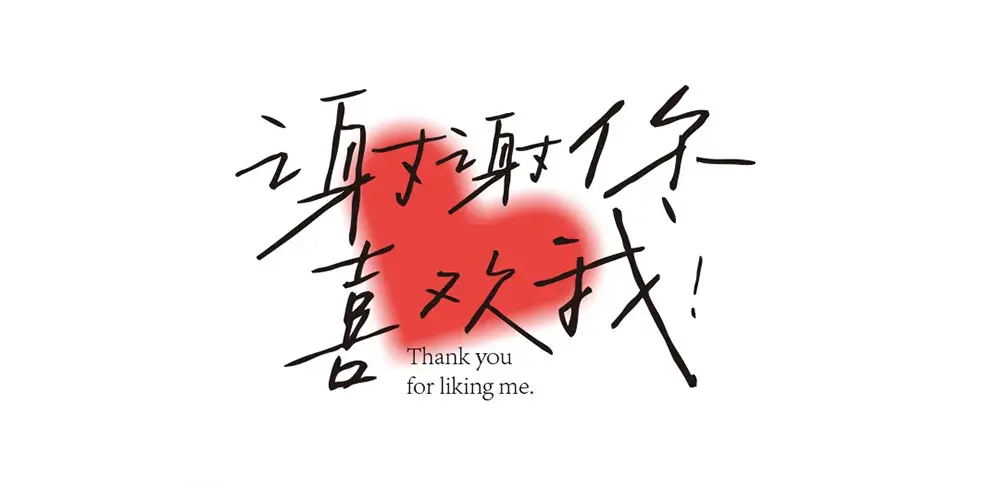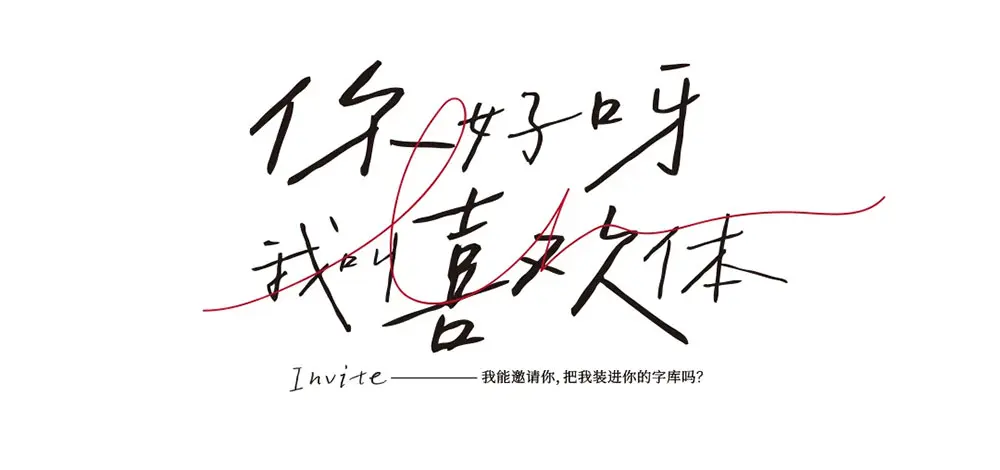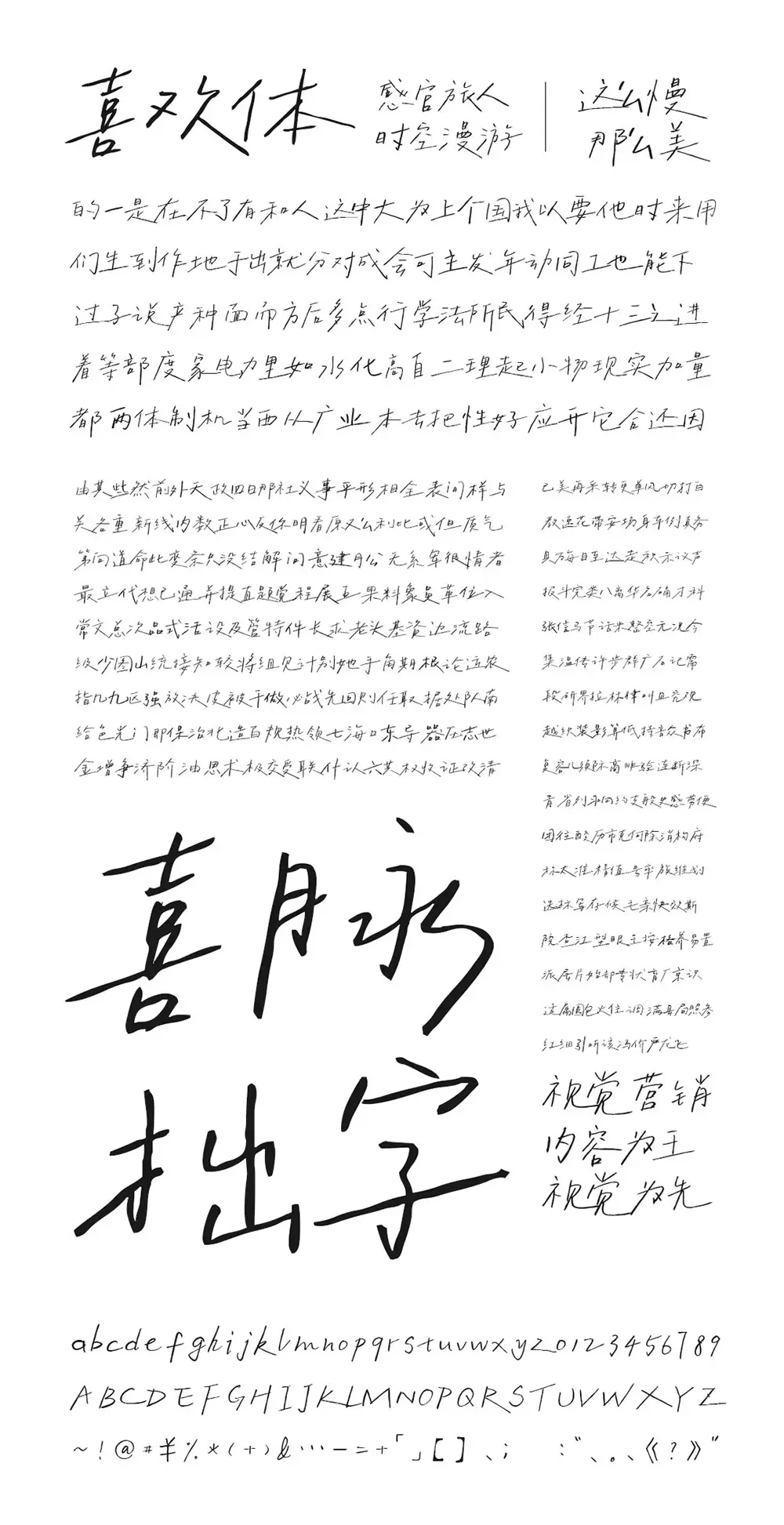
21年我們發佈了第一款免費公益字體——字制區喜脈體,至今已經過去3年了。
喜脈體發佈以來,出乎意料的受到各界歡迎,央視TV、奧運會、BAT、字節、小紅書、各大明星電視機、還有平時逛超市貨架上的商品上均有展露,就連到朋友開的咖啡店都看到杯套上用的是喜脈體................,也許這就是普通人的自豪感。
去年,在練習iPad手寫的時候,想著要不索性寫一套拙字吧,好看的寫不出,但自然文藝有溫度的還是可以試試的。
於是我借鑑兩款市面上已發佈的手寫體,進行了兩者風格的結合,但最終寫了一套今天要送給大家的這份禮物,它叫——字制區喜脈喜歡體。
總字數:7367,英文:104,數字:93,標點:67,符號:44,應該是涵蓋了日常所有常用字符了。
字體風格比較文藝、自由,比較適合作為字數少的大標題使用,像自媒體封面標題/字幕、音樂專輯、電影海報、雜誌、照片排版等,都是非常匹配的場景哦!